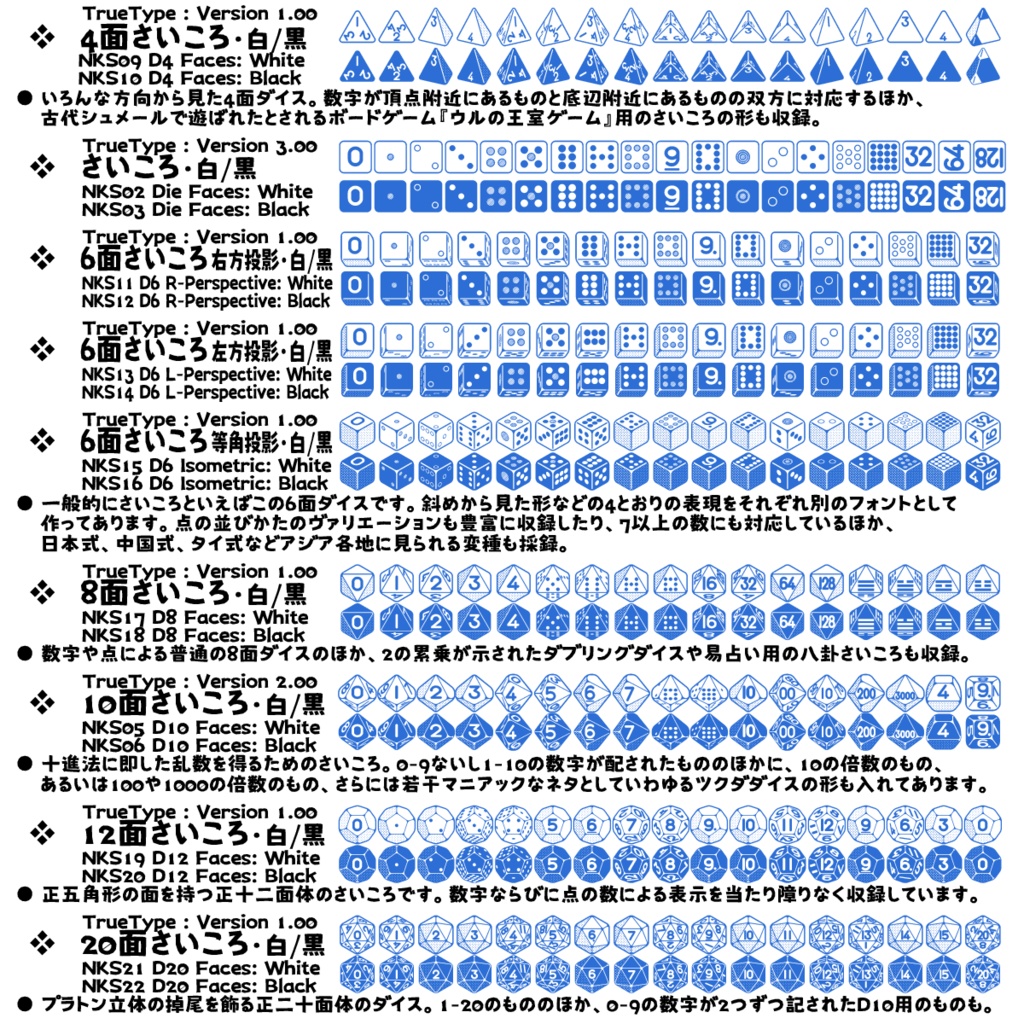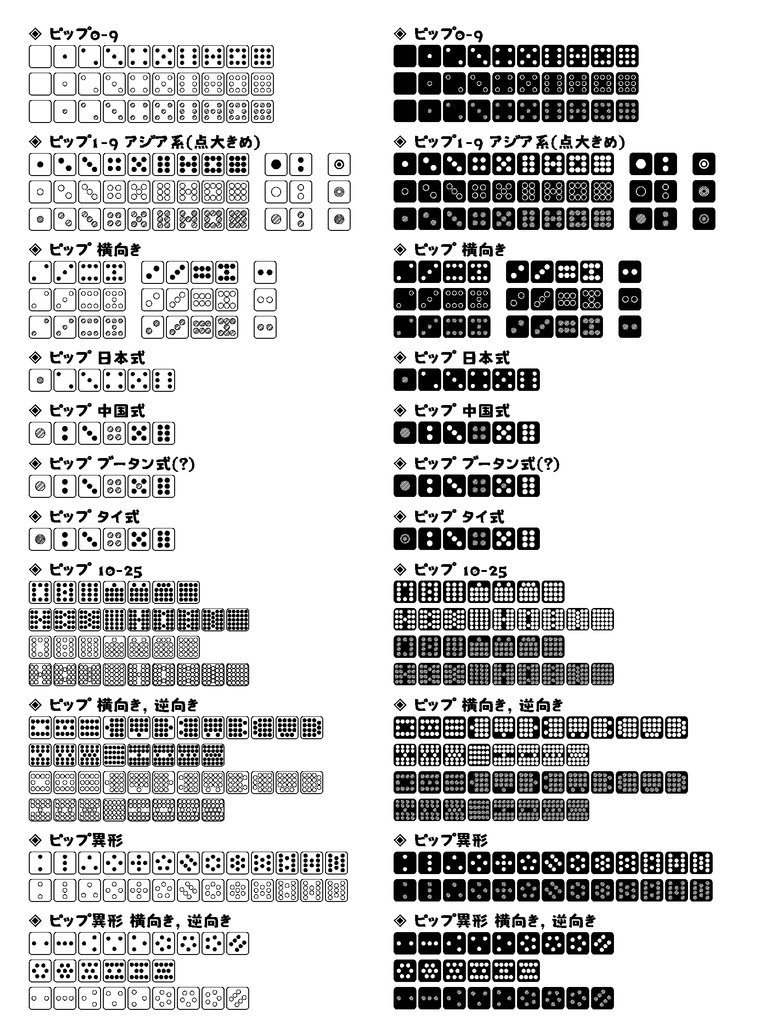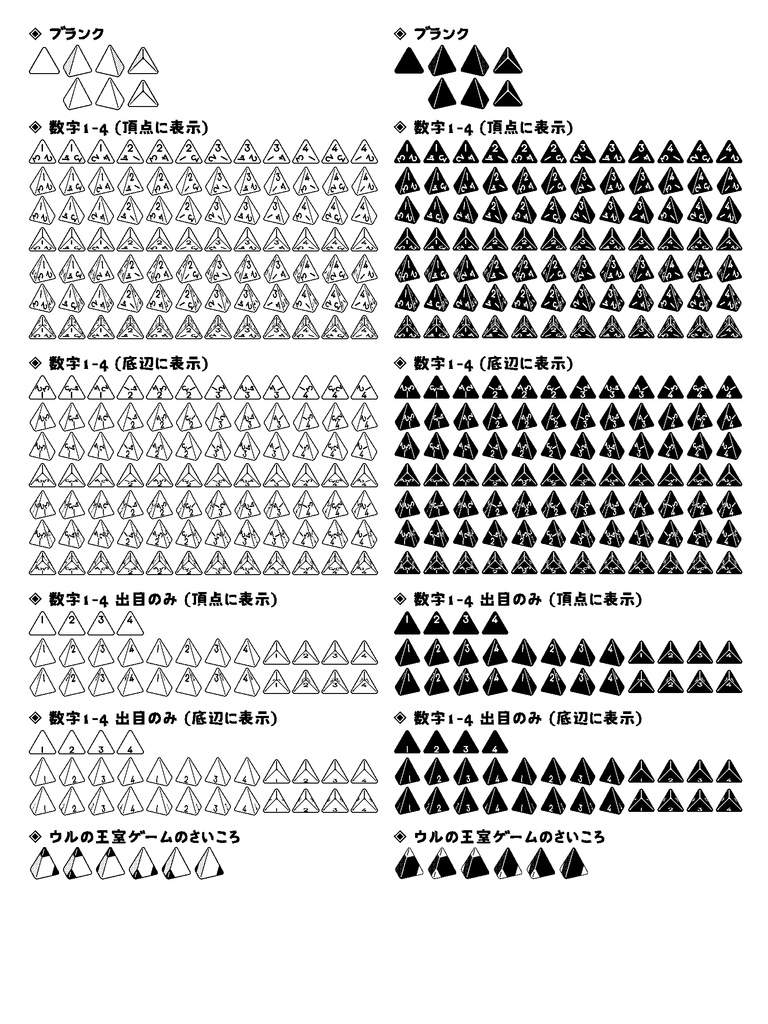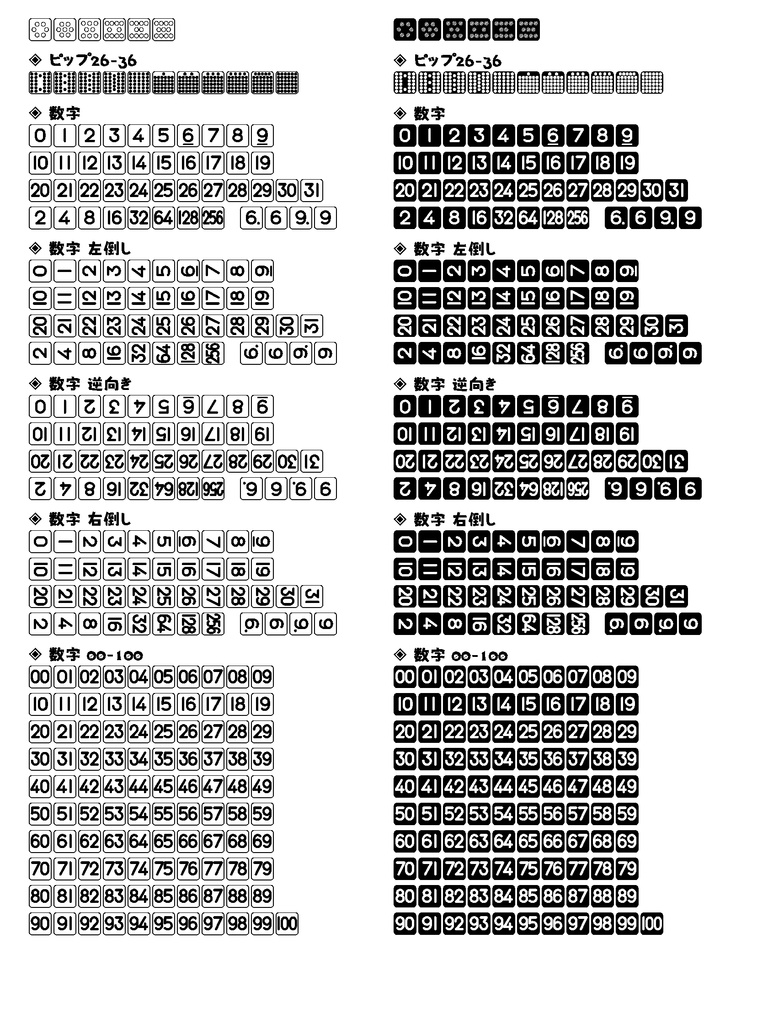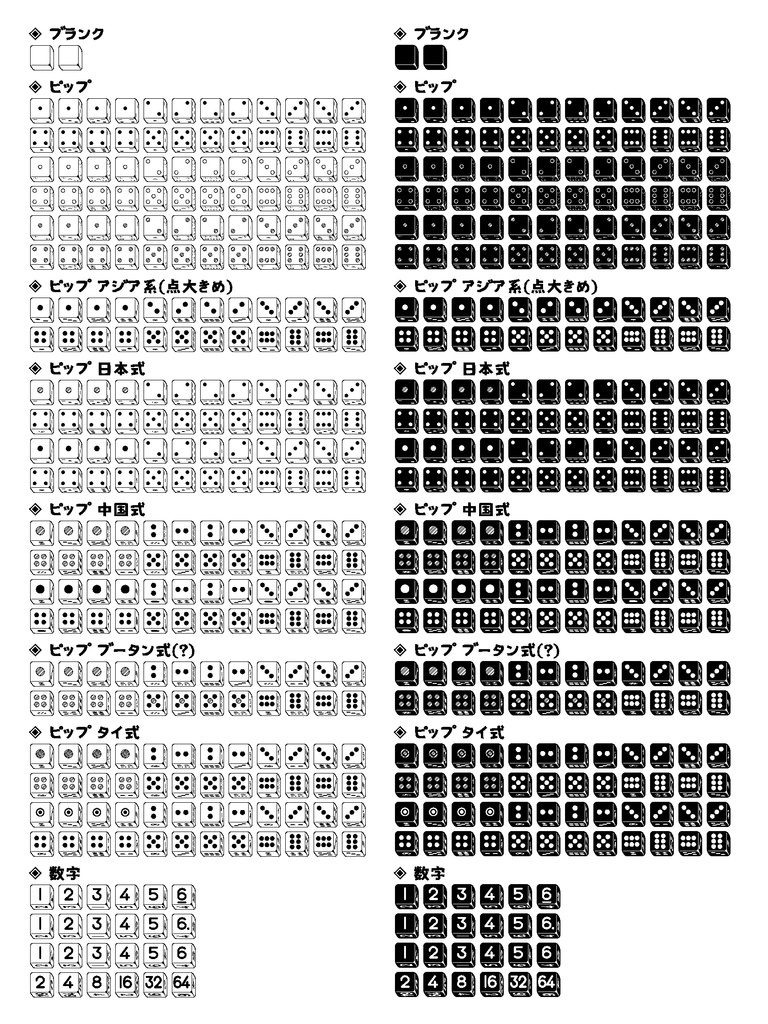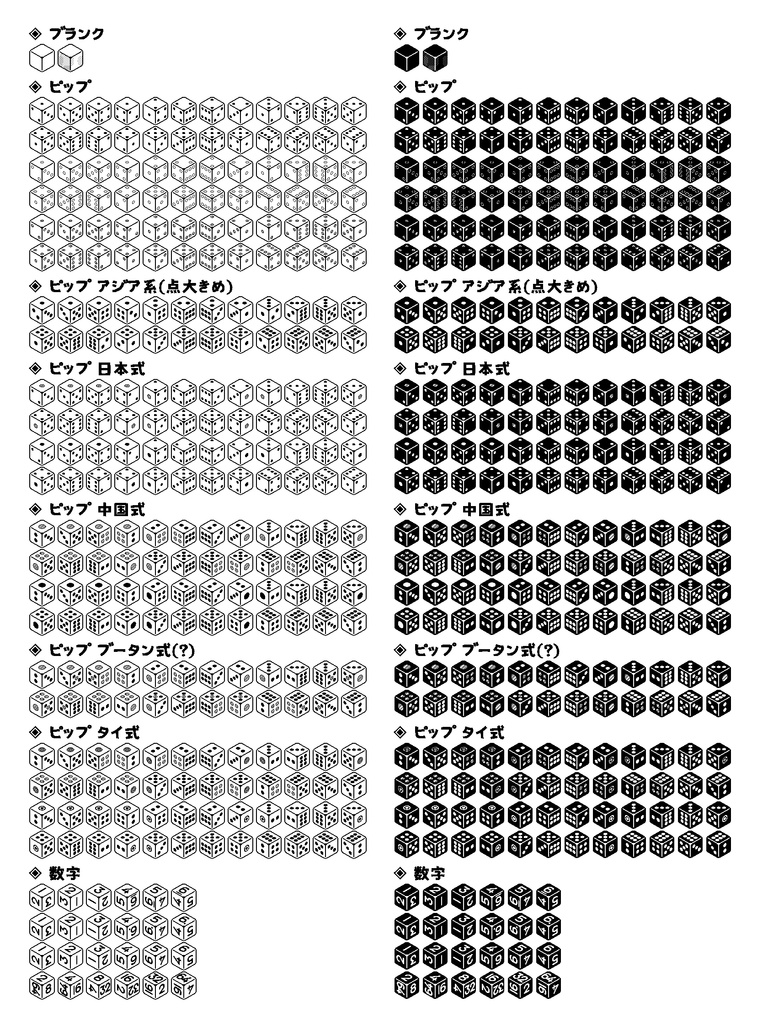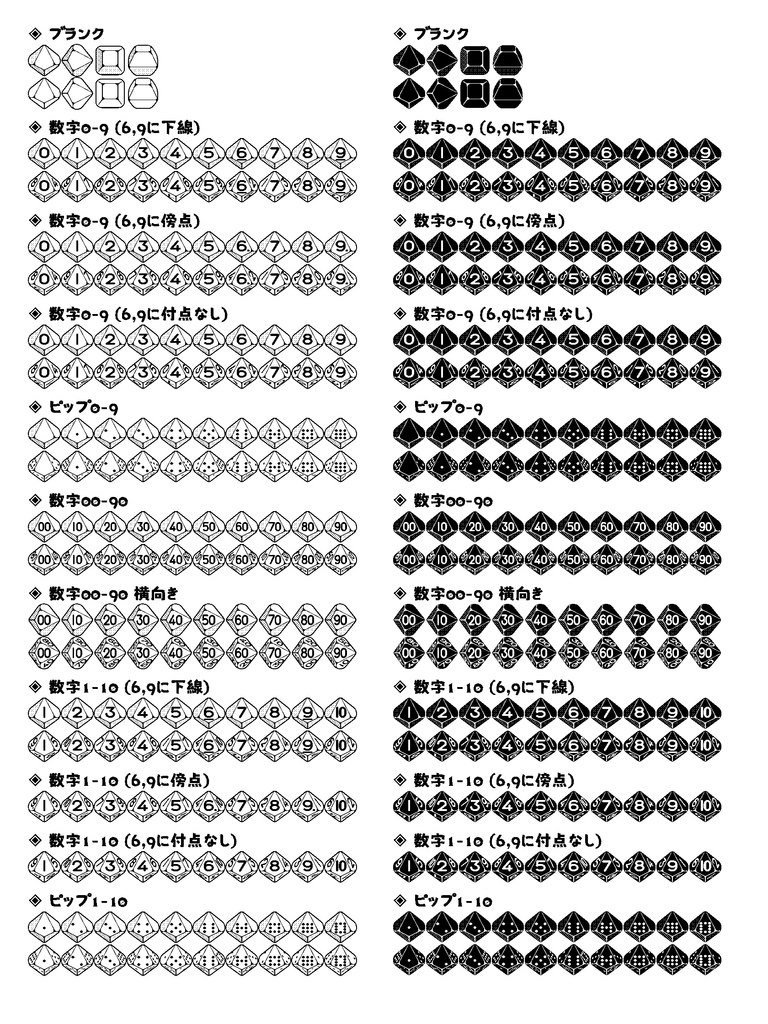
波間のかけひきフォント集・さいころ玉手箱 プラトニカ
NAMIMA NO KAKEHIKI FONT COLLECTION - THE DICEFUL DICEY CASKET: PLATONIKA 🔤 六面はもとより、四面体から二十面体まで、多面体ダイスのいろいろな外観を表情豊かに収録したフォント集です。 卓上ゲーム関係の文書の作成や装飾などもろもろに、ぜひご活用ください。 主にラテンアルファベットの領域や、私用領域(外字)のところにグリフを収めています。 ❖ 当フォント群の一般的な目的での使用 (文書や画像の作成、装飾としての利用など) は私用、同人、商用を問わずご自由にどうぞ。 ✽ 形式: フォントはTrueType、添付資料はPDF